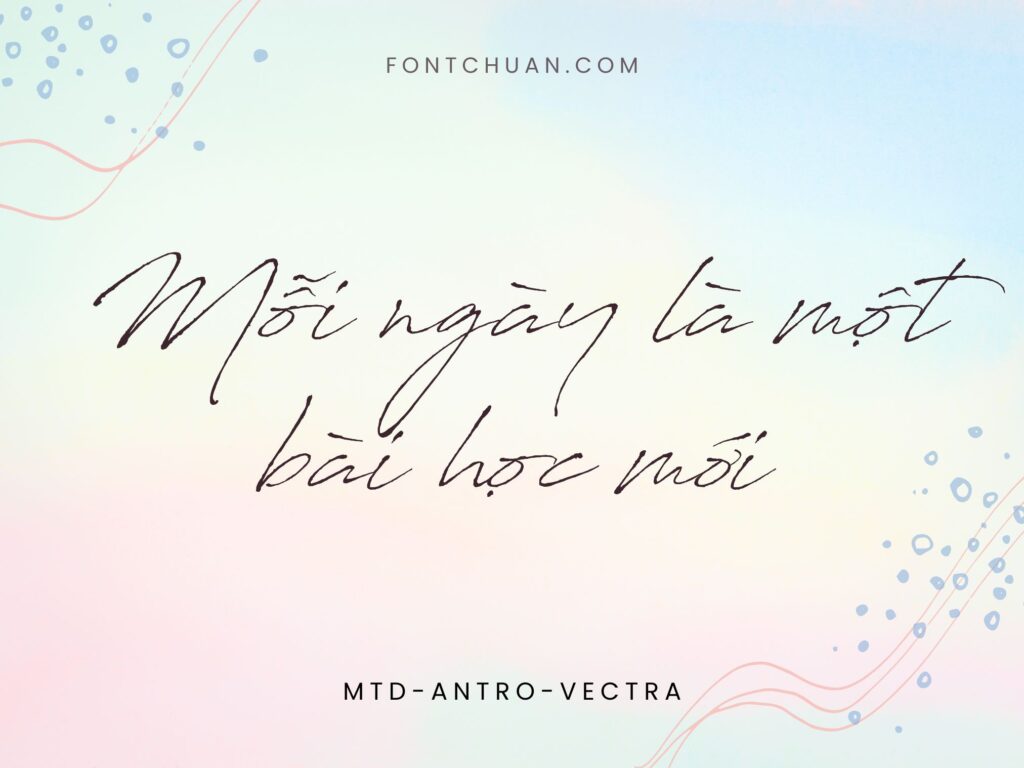
Font Antro Vectra là một kiểu chữ viết tay hiện đại, được thiết kế bởi Youssef Habchi. Với các đường nét uyển chuyển và tinh tế, Antro Vectra mang lại sự thanh lịch và độc đáo cho các thiết kế, đặc biệt khi được ứng dụng như một Font logo để tạo dấu ấn thương hiệu cá nhân hoặc doanh nghiệp.
Phiên bản Antro Vectra đã được Việt hóa bởi Mộc Hạ, hỗ trợ đầy đủ tiếng Việt cùng hơn 35 ngôn ngữ khác như Anh, Pháp, Tây Ban Nha, Đức và Ý, mở rộng khả năng ứng dụng trong thiết kế đa ngôn ngữ. Font này đã được thành viên Font Chuẩn sưu tầm và chia sẻ, đáp ứng nhu cầu của cộng đồng thiết kế. Với thiết kế bao gồm các ký tự viết tay mềm mại và ligatures độc đáo, Antro Vectra phù hợp cho các ứng dụng như thiết kế logo, thiệp mời, bao bì sản phẩm và các ấn phẩm quảng cáo. Các ngành nghề như quảng cáo, giáo dục, công nghệ và ẩm thực có thể tận dụng font này để tạo ra thiết kế ấn tượng và thu hút.